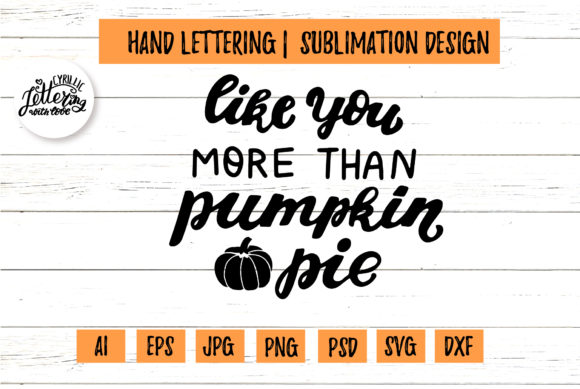
Like You More Than Pumpkin Pie
Mencari elemen reka bentuk yang sesuai boleh menjadi mencabar, tetapi Like You More Than Pumpkin Pie menawarkan koleksi luar biasa yang menaik taraf karya anda serta-merta.
Sama ada anda mencipta produk POD (Print on Demand), jemputan perkahwinan atau grafik media sosial, Like You More Than Pumpkin Pie amat bersesuaian.